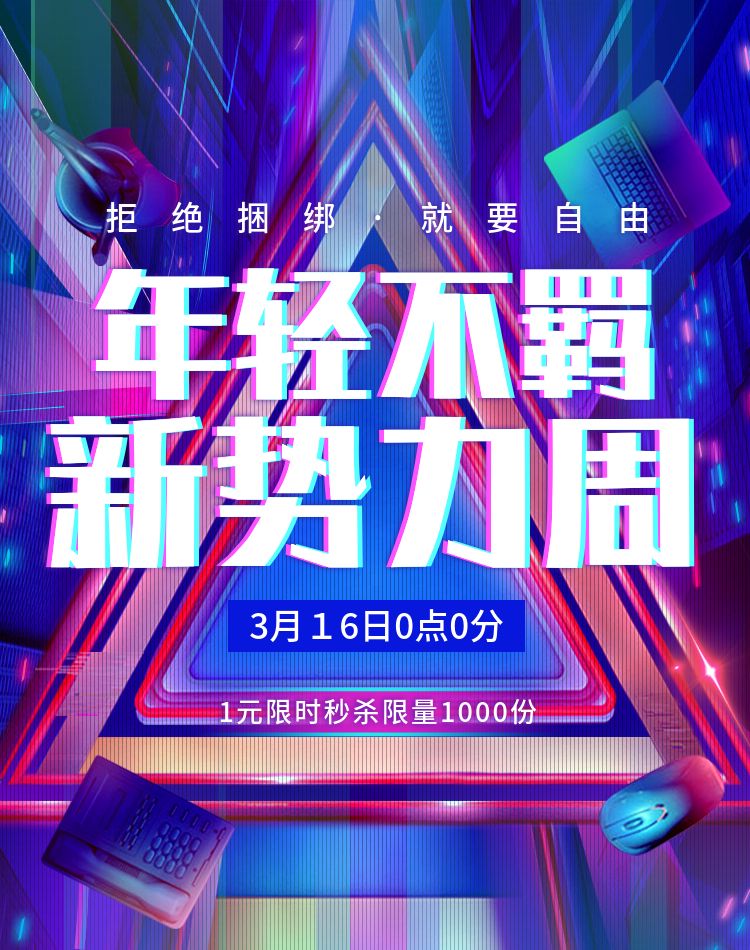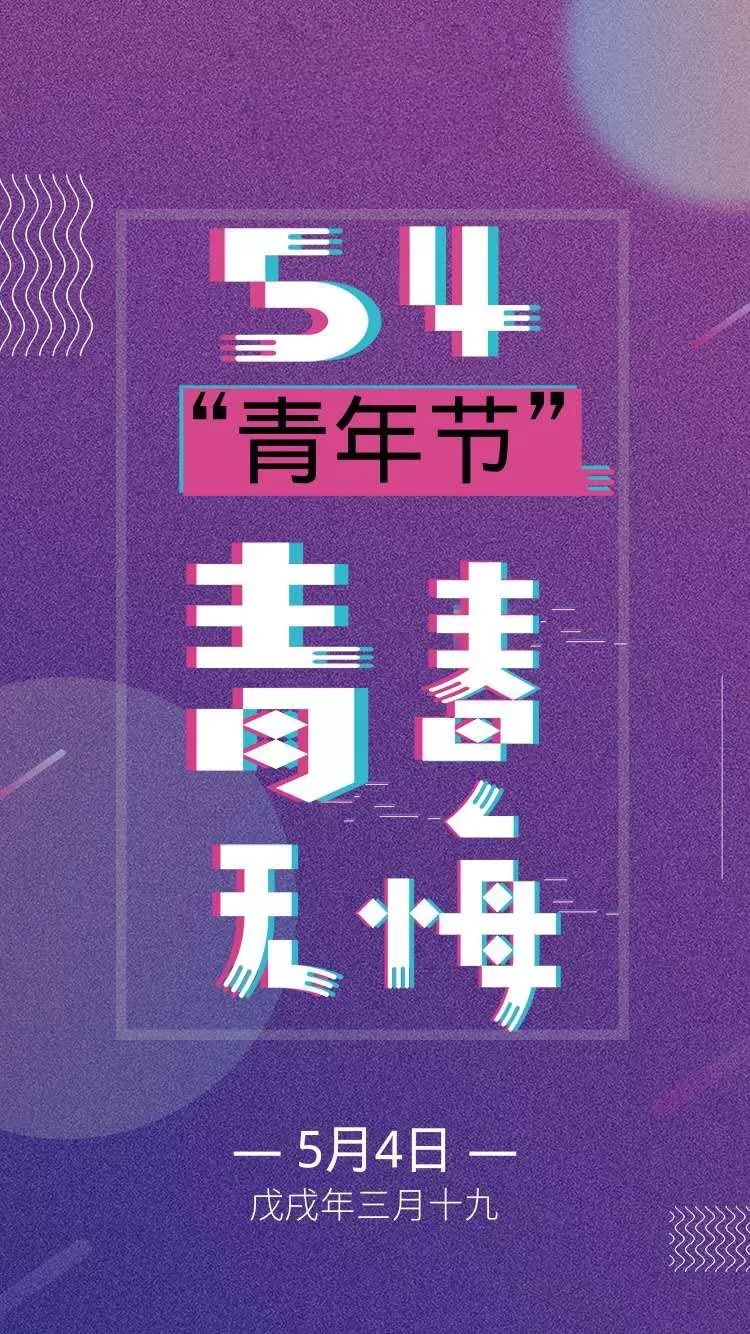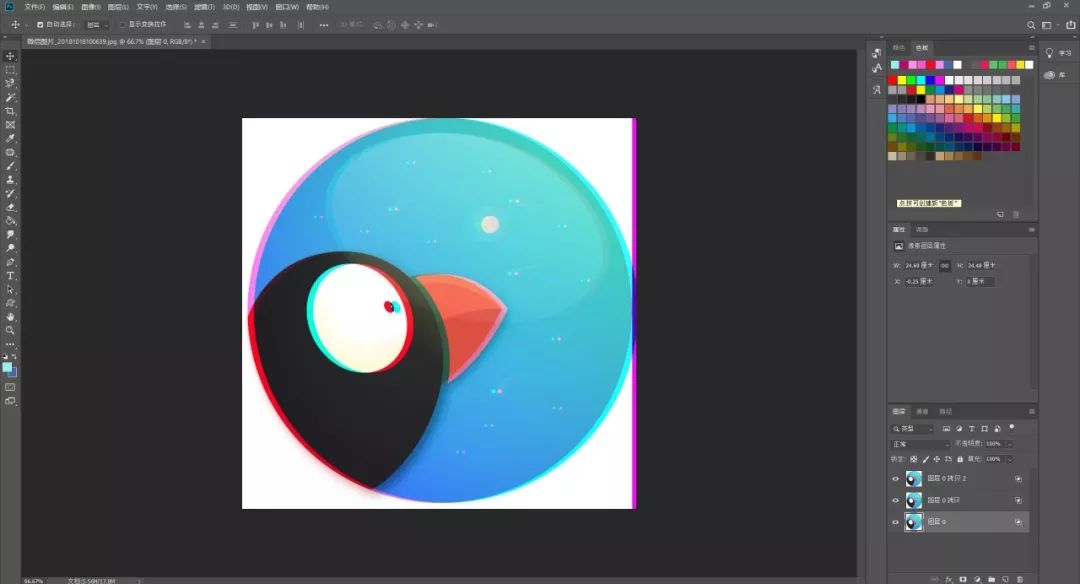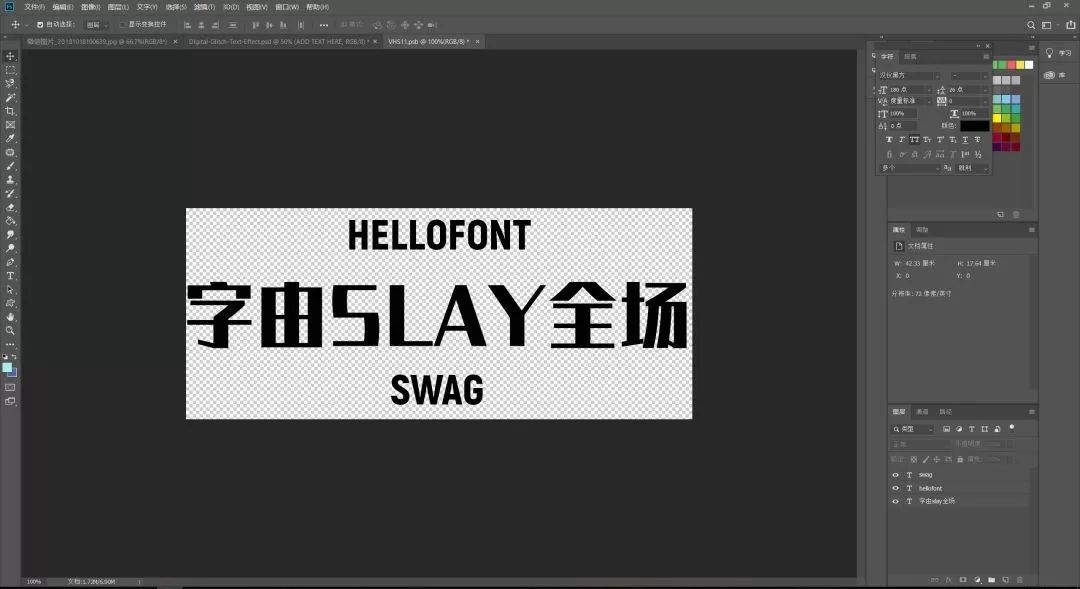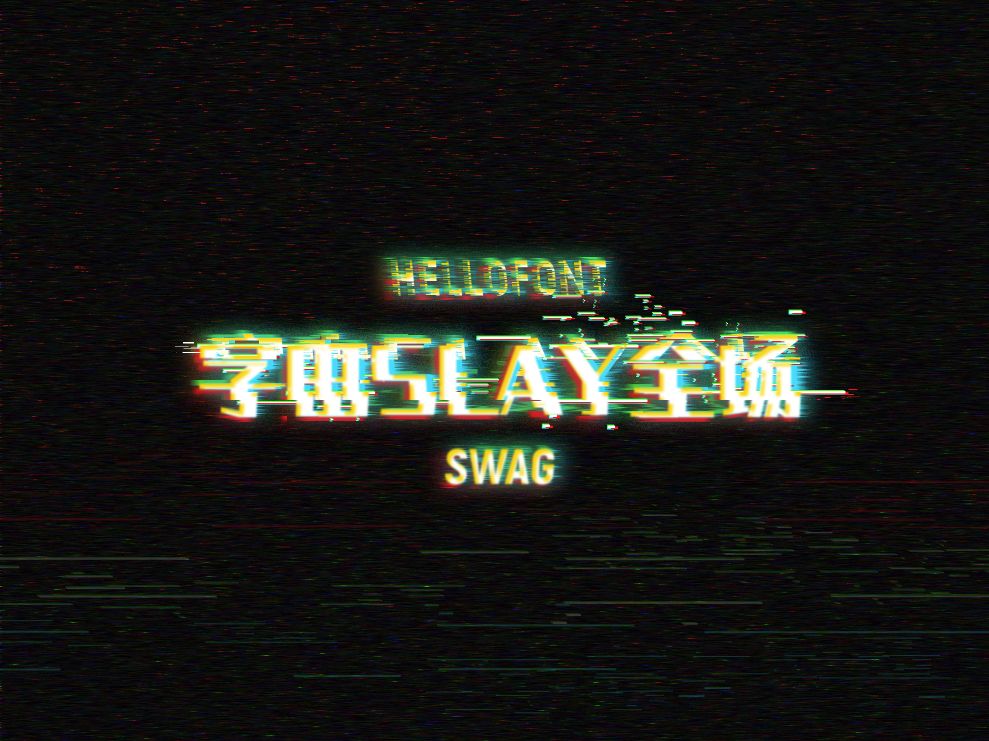
故障效果怎么玩?教你如何制作故障效果
这几天看到好多的“抖音字”,虽然我不玩抖音(只玩小绿书),但看起来还是很潮的,符合我叛逆的路子~
其实这就是小时候看电视花屏的效果,但现在作为一种glitch art流行了,果然bug不全一无是处啊!
要说起它的发展历史呢,那就太冗长了(主要是我憋不出来),还是看看《攻壳机动队》的电影海报吧!
有点感觉了嘛,很酷,又有未来感,完全符合当下年轻人的口味,所以你买买买的时候能看到它。
刷网页的时候,也能看到它的身影。
有时候只是字体上的一点小变化,看起来就大不一样!
所以你想知道怎么做的嘛,教你个最简单的,打开一张清纯的字由小鸟~
分别复制两个图层,作为孪生兄弟~
每个图层的通道,有一个不勾选,比如图层0,只有R、G,以此类推~
剩下的每一层,你左右轻移就好了,是不是一下就变成抖音版字由小鸟了。
当然这只是基础眼花版,主要红蓝两色错位~
想高级一点,比如下面这种,就需要更细致地P了。
这里给你推荐一个网站https://photomosh.com/,可以直接生成。
如果只想局部变换,比如icon,也可以去这里https://illustrio.com/玩玩,它还有很多不同的效果。
怎么能忘了最重要的字体,我找了个特效包,中文用的是汉仪黑方,英文用的Akrobat,试试看~
哇,真是不止抖三抖,气场全开啊!